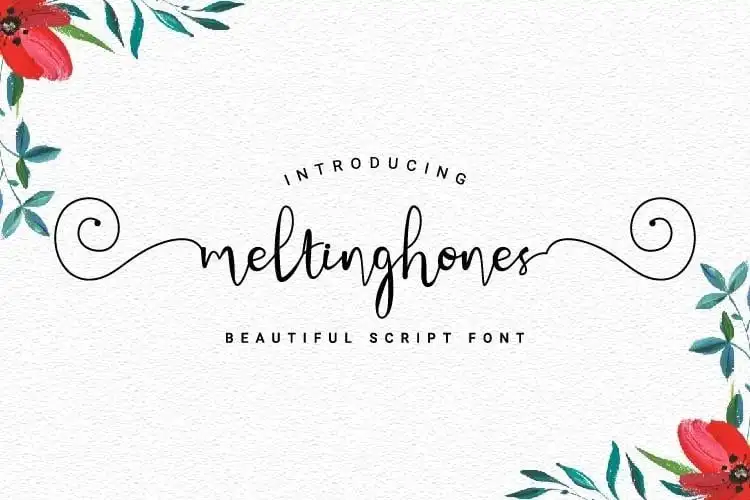
A fonte ‘Meltinghones Calligraphy Font’ é uma bela tipografia para escritura calligrafia, criada pelo designer prioritype e disponível no site 99designs. Esta fonte elegante e delicada se destaca pela sua capacidade de atender a uma variedade de necessidades gráficas, seja em impressão ou mídia digital. Perfetamente adaptável para diversos tipos de projetos, como boutiques e salões, jóias femininas, convites de casamento, cartões de visita, marcas fotográficos, roupas criativas e posts artísticos. A fonte suporta multilinguismo, o que a torna ainda mais versátil. Aproveite esta fonte elegante para suas próximas criações gráficas em projetos variados. Com uma aparência de luxo e elegância, ‘Meltinghones Calligraphy Font’ certamente enriquecerá seus designes. Para visualizar a diversidade de estilos desta fonte, você pode consultar as imagens de pré-visualização disponibilizadas por 99designs.